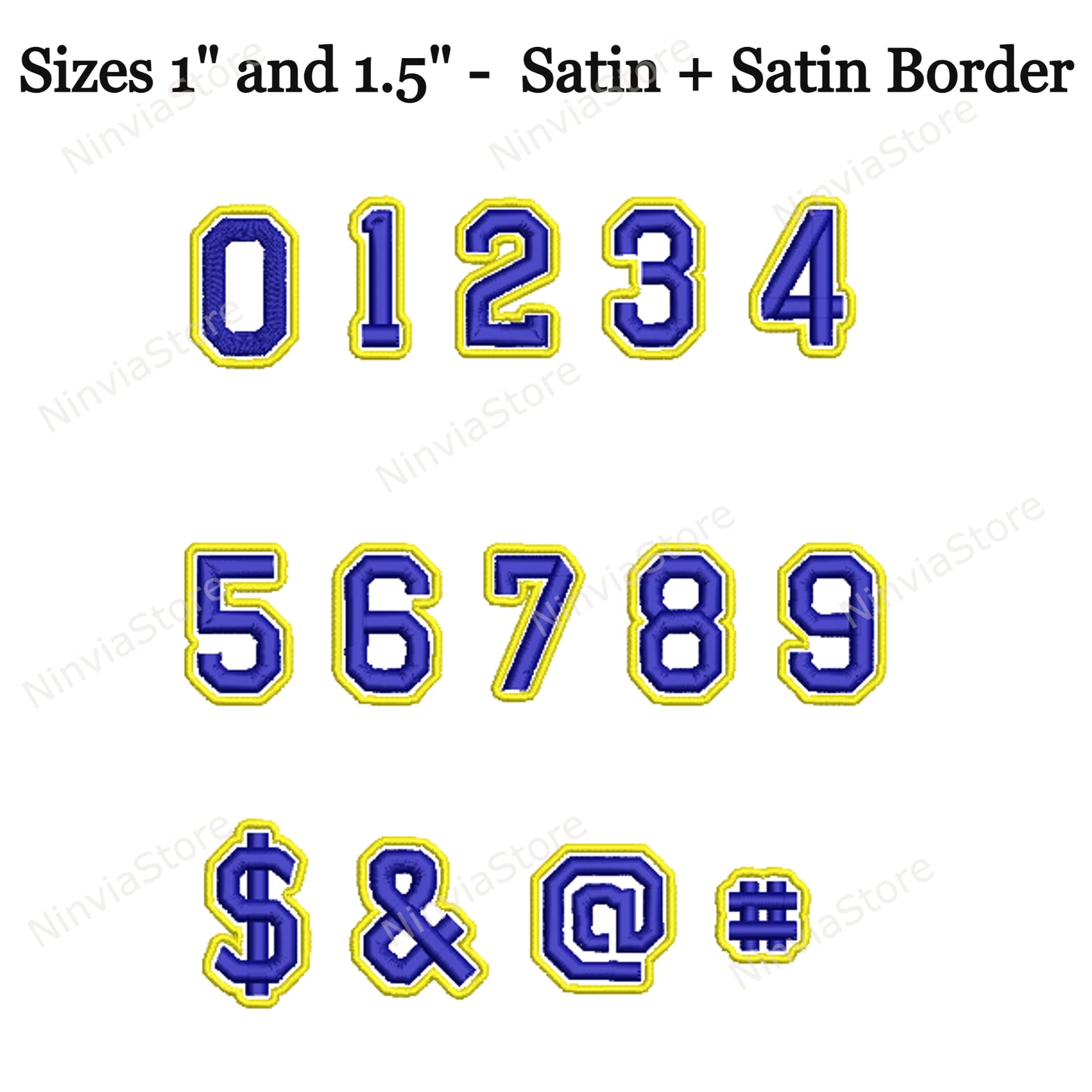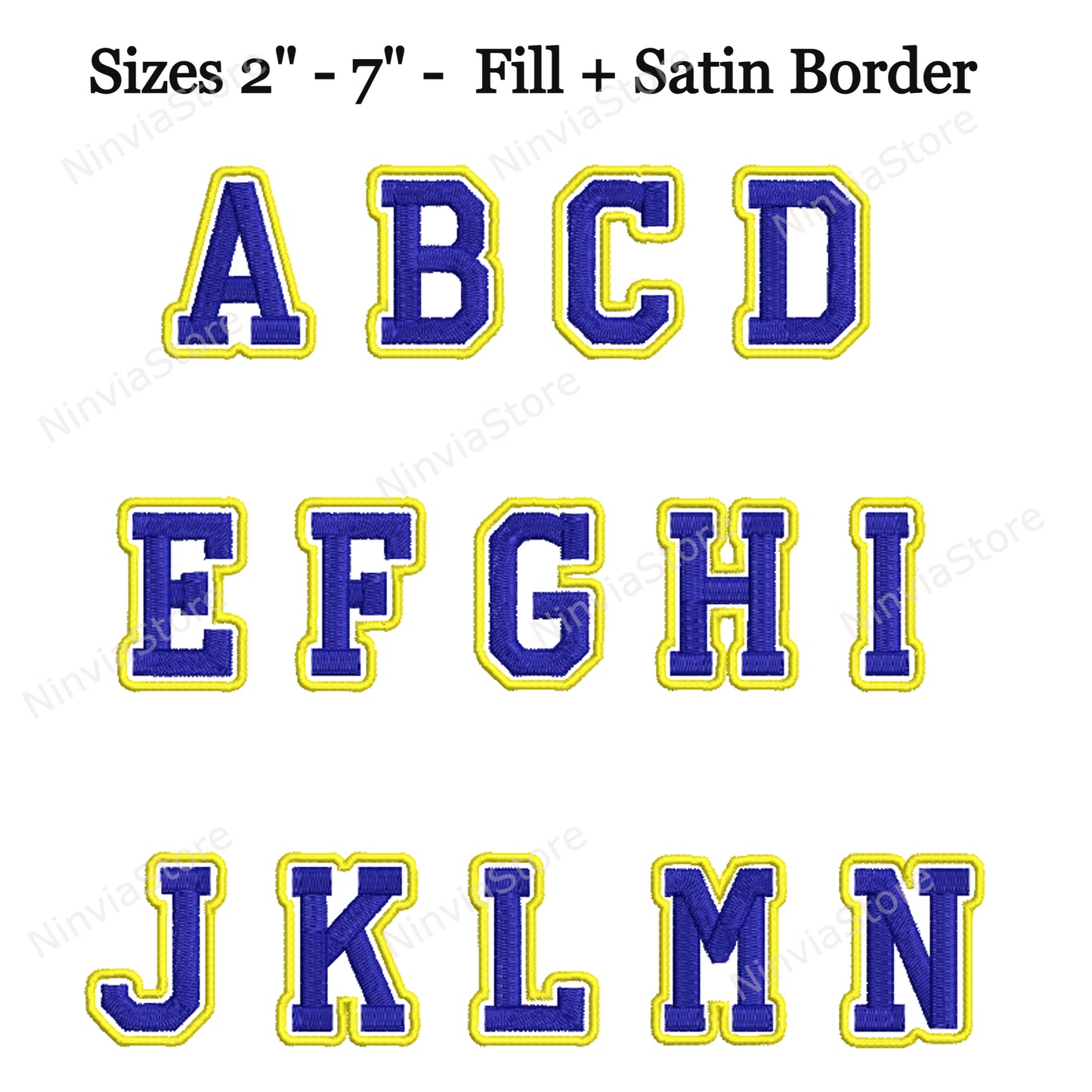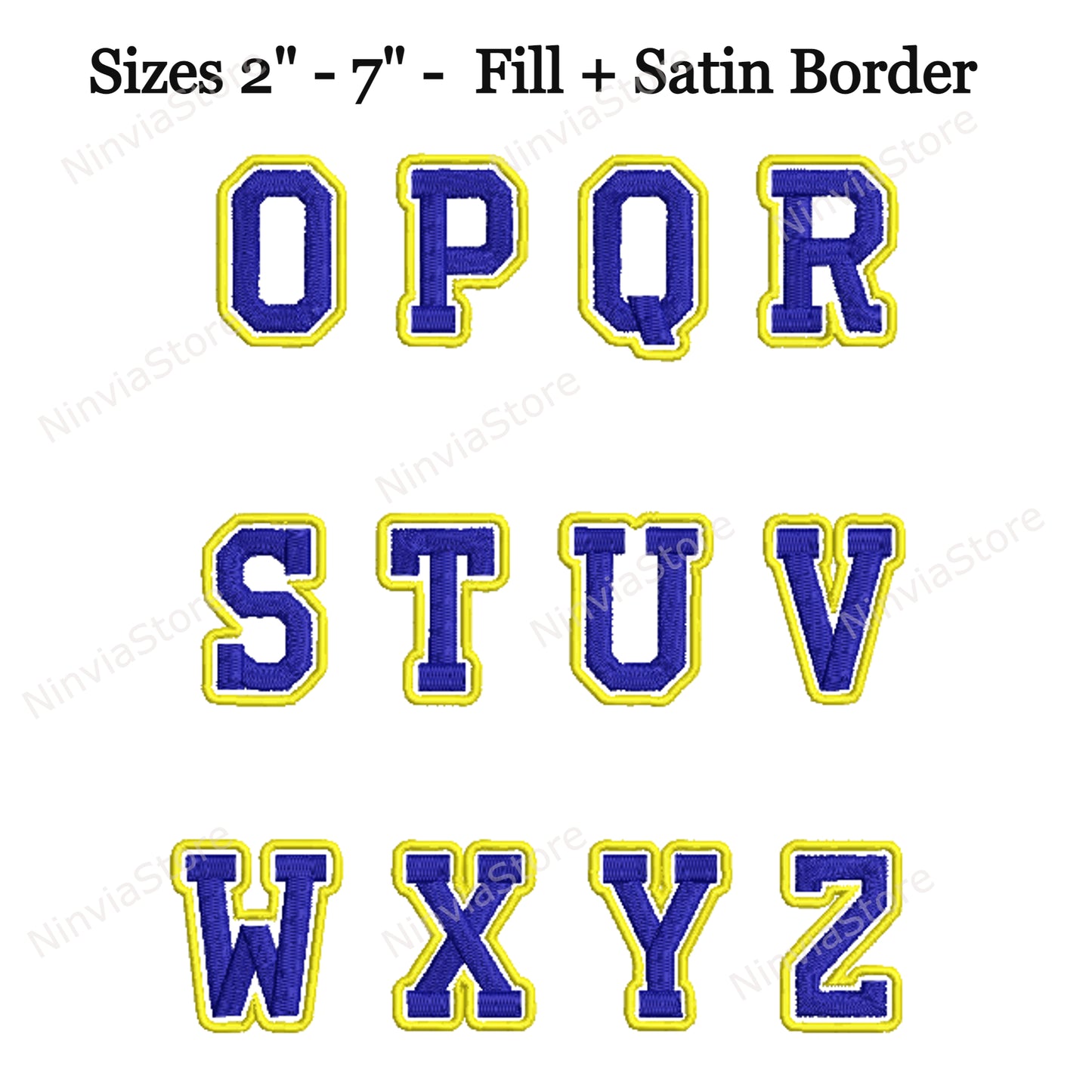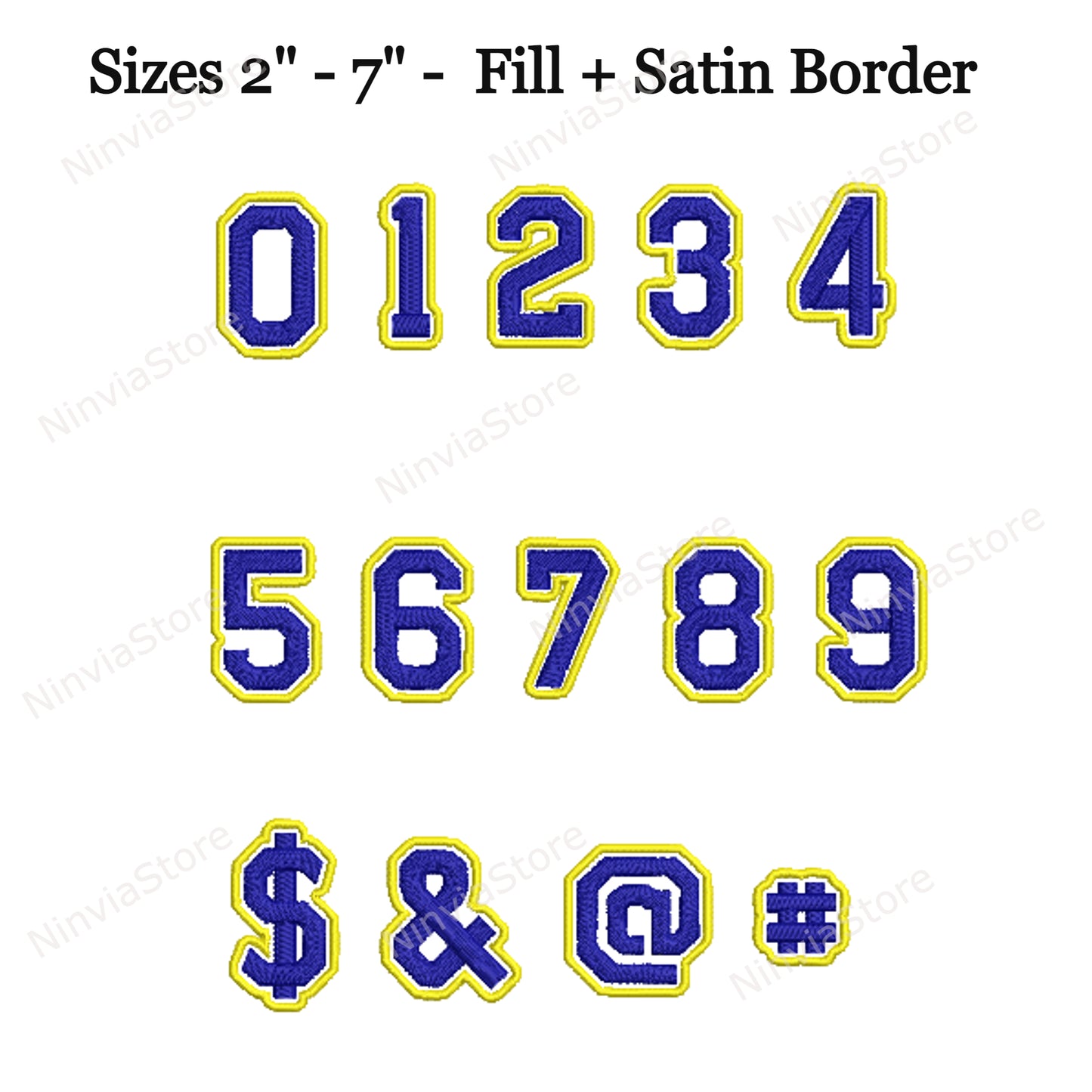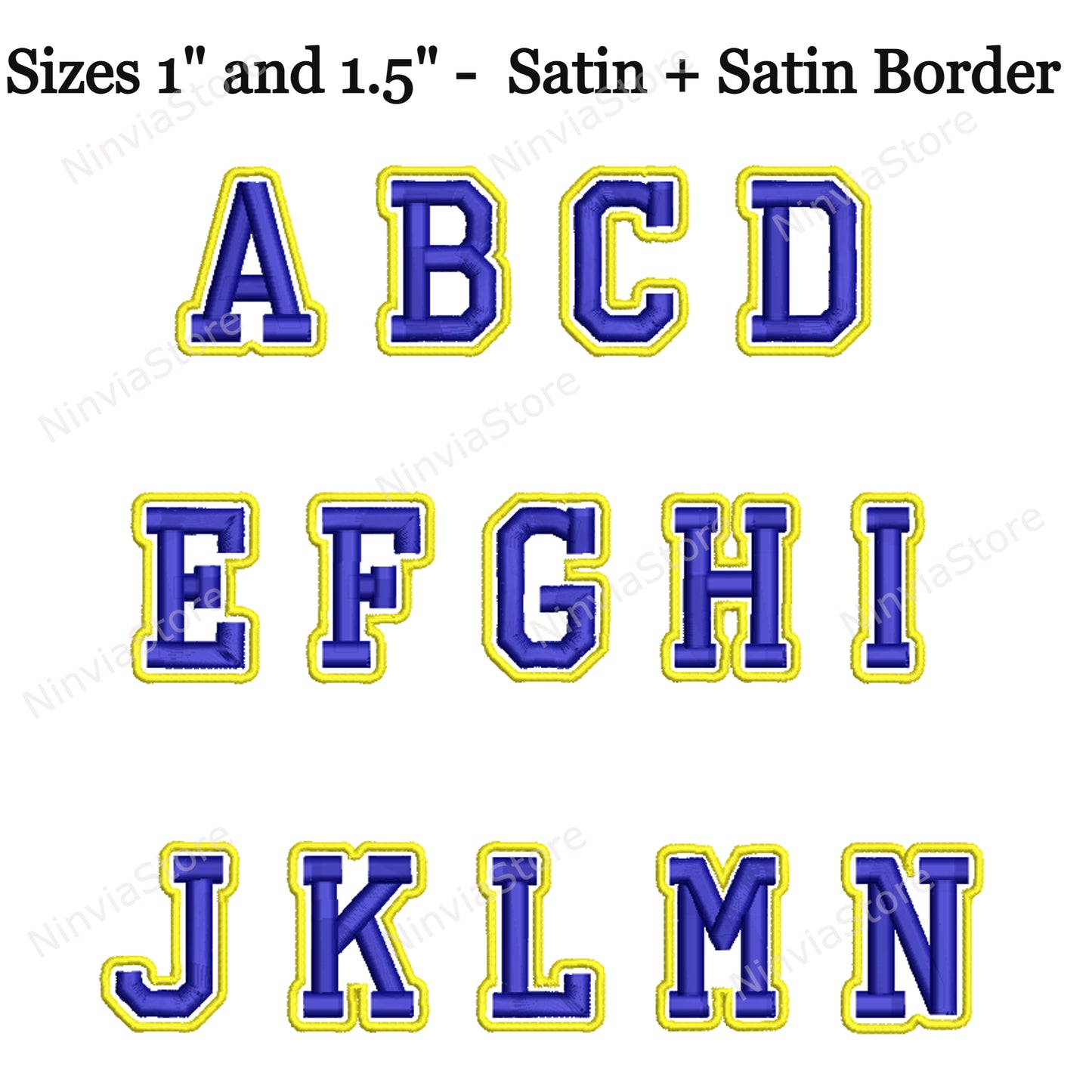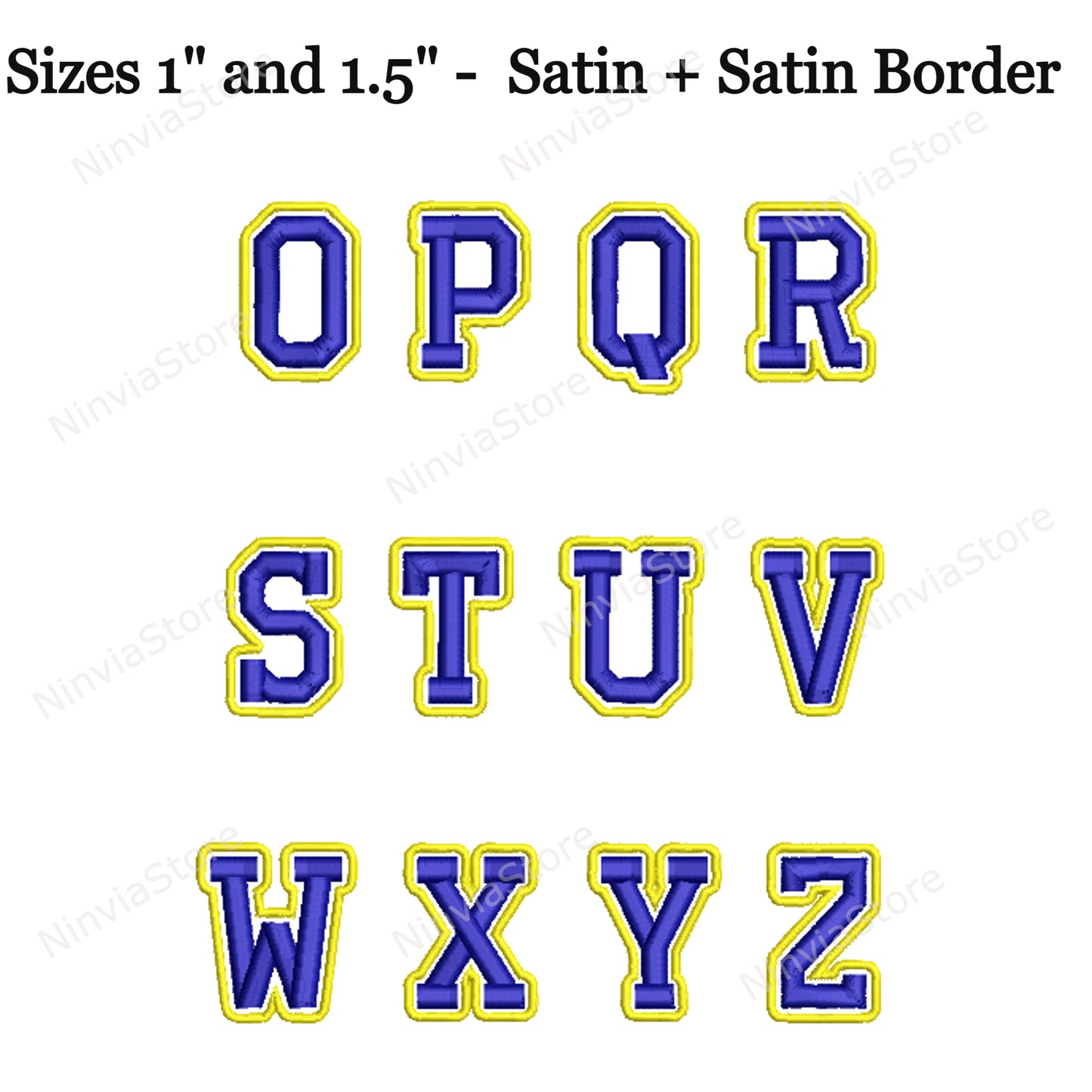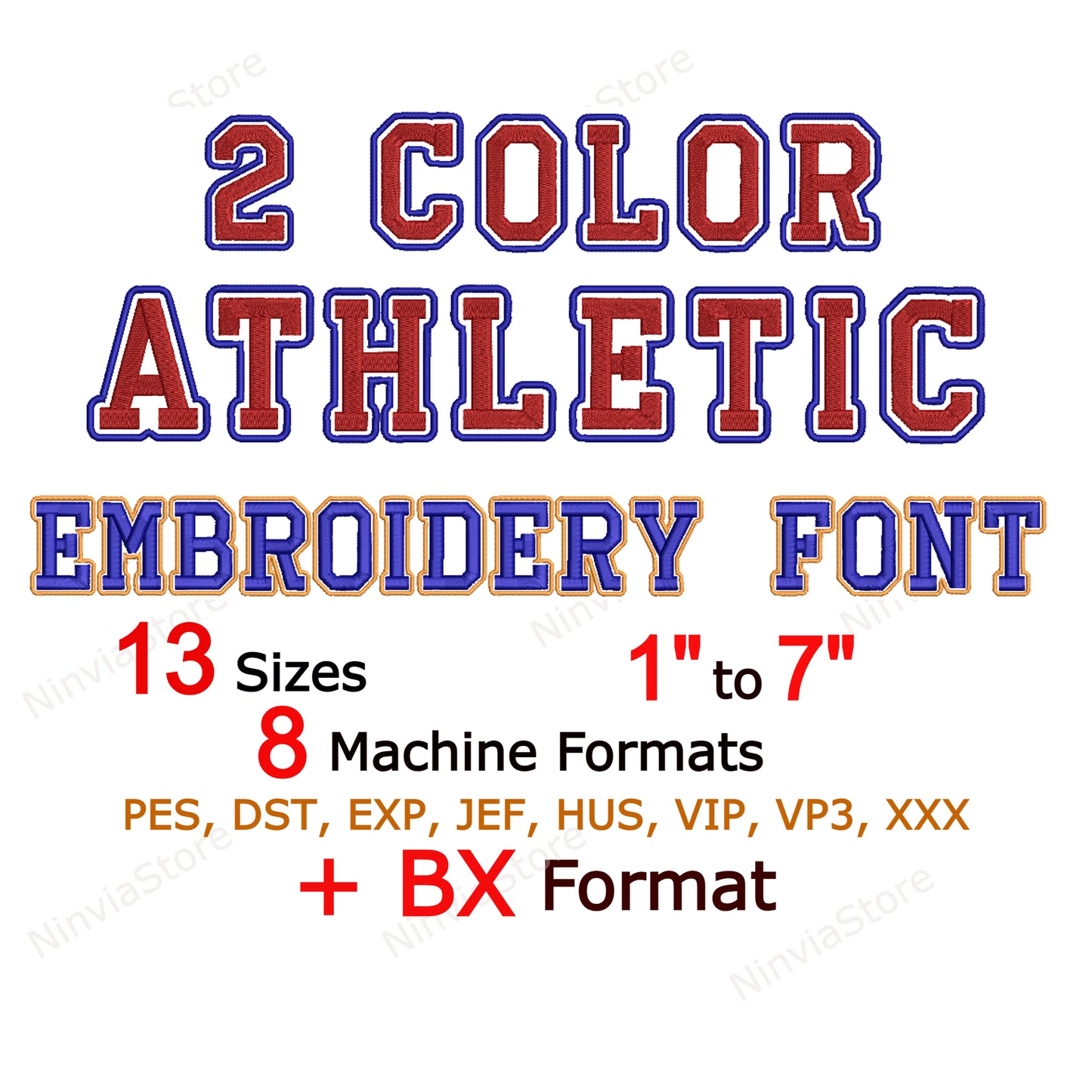
2-farbige Athletic-Maschinenstickschrift, 13 Größen, 8 Formate, College BX-Schriftart, PE-Schriftart, Monogramm-Alphabet-Stickmotive
Die zweifarbige Athletic-Monogramm-Stickschrift steht zum sofortigen Download zur Verfügung.
2 Zoll – Füllstich + Satinstich
2,5 Zoll – Füllstich + Satinstich
3 Zoll – Füllstich + Satinstich
3,5 Zoll – Füllstich + Satinstich
4 Zoll – Füllstich + Satinstich
4,5 Zoll – Füllstich + Satinstich
5 Zoll – Füllstich + Satinstich
5,5 Zoll – Füllstich + Satinstich
6 Zoll – Füllstich + Satinstich
6,5 Zoll – Füllstich + Satinstich
7 Zoll – Füllstich + Satinstich
40 Designs
4 Symbole